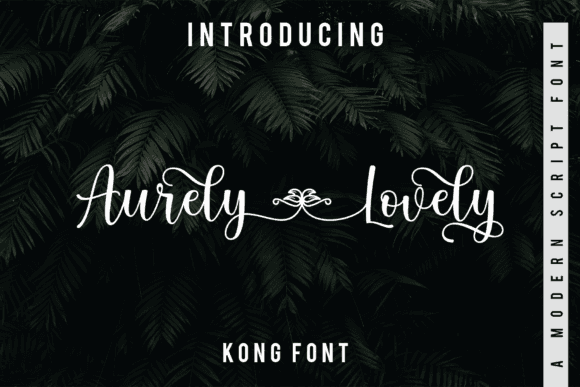
Una fuente realmente encantadora para manualidades, logotipos y proyectos de impresión.
Aurely Lovely es una fuente caligráfica moderna y alegre que aporta encanto a cualquier proyecto. Perfecta para artesanos y diseñadores , añade un toque de elegancia y diversión a tu trabajo. Ya sea que estés creando invitaciones, pósteres o gráficos para redes sociales, esta fuente hará que tus proyectos destaquen.